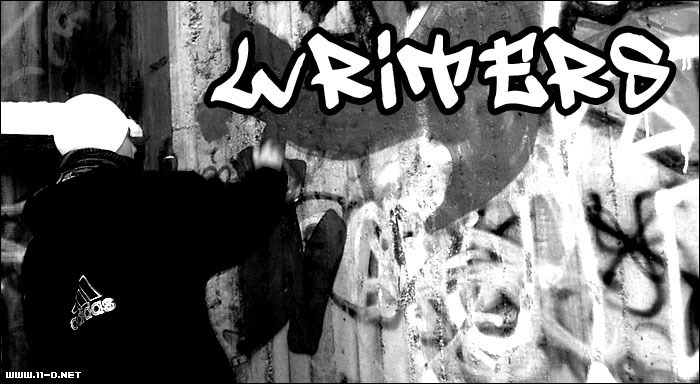
Writers Bold di Johan Waldenstrom è un font graffiti gratuito che racchiude l'energia grezza del lettering a pennarello in forme massicce e angolari. Le lettere puntano su giunture affilate, spessori irregolari e tratti netti, dando all'intero carattere un ritmo street che appare improvvisato ma al contempo compatto.
Si adatta perfettamente a poster, branding per il mondo skate e musicale, titoli di volantini, copertine di fanzine e cartelli dove si desidera quell'attitude urbana grezza senza però scivolare nel cartoon. Essendo un font gratuito, è ideale anche per loghi brevi, monogrammi e capilettera, poiché le silhouette frastagliate e la spaziatura compressa assicurano un impatto visivo d'effetto anche con poche lettere.